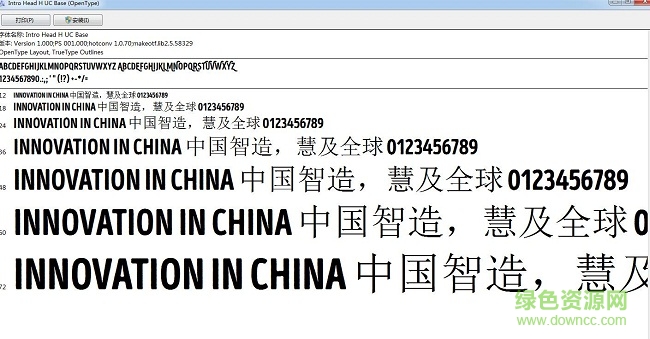
introheadhuc字體是一款不錯的英文字體,字體結(jié)構(gòu)簡潔爽朗,線條搭配和諧,適用于期刊、雜志、廣告設(shè)計、文章排版等各個領(lǐng)域,有需要者歡迎免費下載!
在文字設(shè)計中,美不僅僅體現(xiàn)在局部,而是對筆形、結(jié)構(gòu)以及整個設(shè)計的把握。文字是由橫、豎、點和圓弧等線條組合成的形態(tài),在結(jié)構(gòu)的安排和線條的搭配上,怎樣協(xié)調(diào)筆畫與筆畫、字與字之間的關(guān)系,強(qiáng)調(diào)節(jié)奏與韻律,創(chuàng)造出更富表現(xiàn)力和感染力的設(shè)計,把內(nèi)容準(zhǔn)確、鮮明地傳達(dá)給觀眾,是文字設(shè)計的重要課題。